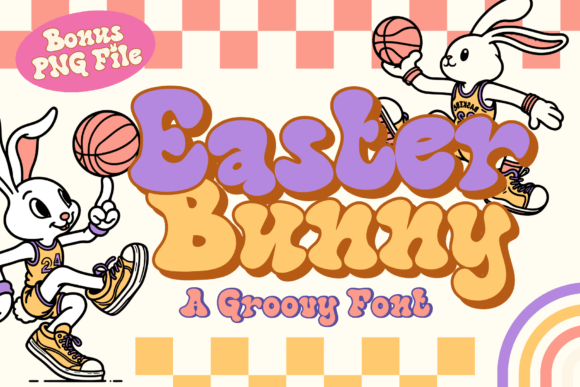
Easter Bunny Font
Easter Bunny Font – الخط المثالي لتصاميم عيد الفصح! ????????
أضف لمسة من المرح والبهجة إلى تصاميمك مع Easter Bunny Font! يتميز هذا الخط بأسلوبه الجذاب والودود، مما يجعله مثاليًا لمشاريع عيد الفصح، مثل بطاقات التهنئة، الشعارات، المنشورات على وسائل التواصل الاجتماعي، التصاميم اليدوية، وأكثر!
✨ مميزات الخط:
✅ تصميم مرح ومناسب لأجواء عيد الفصح ????
✅ يدعم الحروف الكبيرة والصغيرة
اجعل تصاميمك تنبض بالحياة مع Easter Bunny Font واستمتع بإبداع لا حدود له! ????????